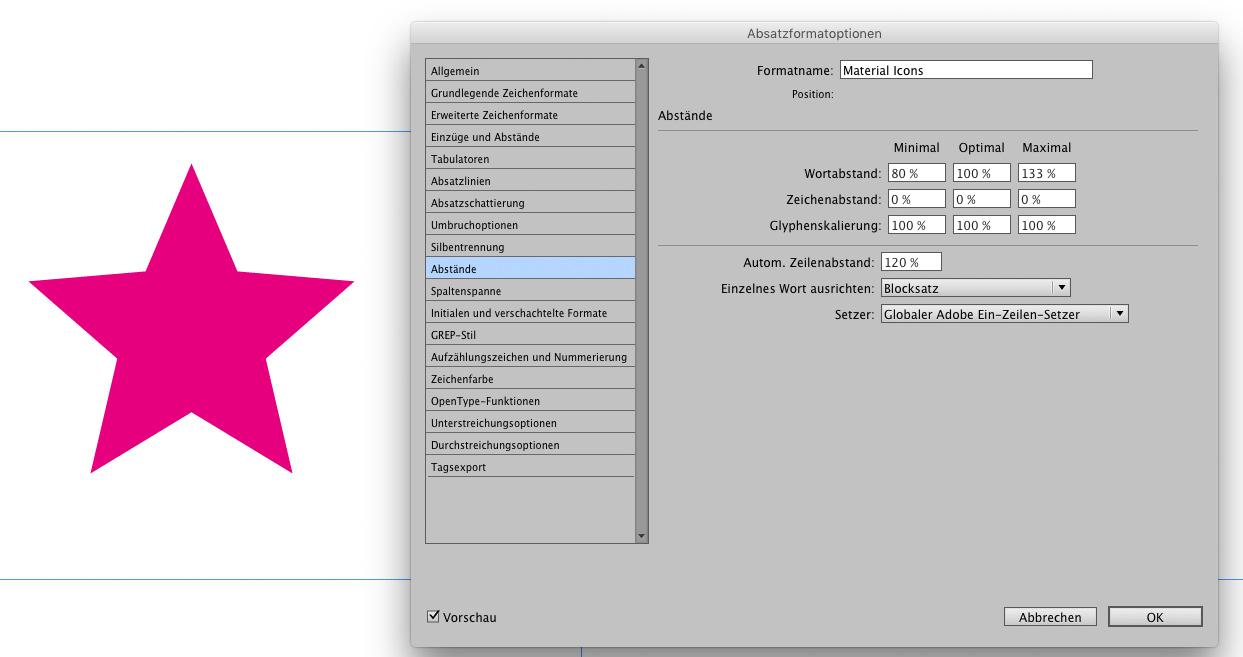
Material Icon Font im InDesign
ich bin ja ein großer Freund des cleveren Iconfonts Ligature Symbols von Kazuyuki Motoyama, weil sich der mit der Ligaturfunktion so wunderbar im InDesign verwenden lässt.
Begriff tippen --> Icon kriegen. Fein.
Deshalb habe ich mich gefreut, als ich gelesen habe, dass der neue Material Icon Font von Google auch so verwendet werden kann. Das funktioniert auch ganz prächtig im Photoshop – leider stellt InDesign* die Zeichen, aus denen die Ligatur zusammengestellt wird, mit kleinen Outline-Rechtecken dar.
Weiß jemand, warum das so ist?
Ich habe die .ttf über die Schriftensammlung aktiviert.
Ich vermute, das liegt daran, daß dem Font das Leerzeichen fehlt. InDesign ersetzt bei einer Ligatur die weggefallenen Glyphen durch Leerzeichen, das in diesem Font, weil es nicht enthalten ist, durch das "notdef"-Kästchen dargestellt wird.
Vermutlich sehr naive Frage an den Profi: Kann man das Leerzeichen denn unproblematisch mit Fontographer oder Glyphs in den Zeichensatz "randengeln"?
Ich vermute, das liegt daran, daß dem Font das Leerzeichen fehlt. InDesign ersetzt bei einer Ligatur die weggefallenen Glyphen durch Leerzeichen, das in diesem Font, weil es nicht enthalten ist, durch das "notdef"-Kästchen dargestellt wird.
Das hatte ich auch erst vermutet, die Vermutung dann aber wieder verworfen, weil .notdef in diesem Font ganz andere Proportionen hat als im Screenshot. Und was das ID-Verhalten angeht, verstehe ich nicht, wie das im Normalfall funktioniert. Entstünden keine Lücken im Text, wenn wegfallende Glyphen durch das normale Leerzeichen (U+0020) ersetzt würden? Oder meinst du etwa das nullbreite »Leerzeichen« (U+2008)? Das bringt aber lange nicht jeder Font mit, sodass dieses Problem wohl öfter auftreten sollte? :-?
Kann man das Leerzeichen denn unproblematisch mit Fontographer oder Glyphs in den Zeichensatz "randengeln"?
Ist zwar etwas spät, aber ich stand gerade vor dem selben Problem und habe einen relativ simplen Workaround gefunden, dass die Icons zumindest korrekt in InDesign verarbeitet werden können – nur leider ohne die praktische Ligaturfunktion, sondern anhand der Glyphen-Palette.
Man kann die Icons in Illustrator "schreiben" und dann per Copy & Paste bei InDesign in den gewünschten Textkasten einfügen. Das Icon wird in InDesign weiterhin als Text behandelt und man kann es in wie gewünscht be- und verarbeiten. Keine Ahnung warum es so funktioniert, aber es funktioniert, wenn auch etwas umständlich!
der Workaround hat beim mir leider nicht funktioniert – ich habe aber gerade durch Zufall die Lösung für das Problem gefunden:
Die rätselhaften Kästchen verschwinden, sobald die Option Globaler Ein-Zeilen-Setzer bzw. Globaler Adobe-Absatzsetzer (über die Absatzformatvorlagen unter "Abstände" oder direkt im Kontextmenü der Absatz-Palette) aktiviert wird.
Die Rechtecke könnten sich überlagende .notdef-Zeichen sein.
Ich vermute, dass das Problem nicht entstünde, wenn die Zeichen a–z und underscore die Breite Null hätten. Sie haben aber eine Breite von 512 Einheiten. Wenn du „lightbulb_underscore“ eingibst, versucht Indesign, das „Wort“ wahrscheinlich zu trennen, bevor das OpenType-Ligatur-Feature greift, denn 20 Zeichen mit einer Breite von 512 Einheiten passen bei einem großen Schriftgrad nicht unbedingt in eine Zeile.
Keine Ahnung, warum die Rechtecke bei dir in Indesign auch unter das Glühbirnen-Icon gezogen werden. Hast du da eventuell am Zeichenabstand (Lauweite/Kerning) rumgespielt und außer dem Code für das Glühbirnen-Icon noch weitere Zeichen eingegeben? Wie auch immer. Das Problem müsste sich leicht beheben lassen:
Du könntest den Font mit TTX dekompilieren und die Breite der Zeichen a–z und Underscore auf den Wert 0 setzen. Ebenso den Wert für lsb (left side bearing). TTX ist kostenlos und im AFDKO (Adobe Font Development Kit for OpenType) enthalten.
Mal abgesehen davon würde es Sinn machen, die Zeichen, die das Ligatur-Feature ersetzen soll, mit einer Outline zu versehen. Sonst weiß man ja gar nicht, welche und wie viele Zeichen man eingetippt hat. Wenigstens ein Bullet als Dummy, damit man weiß, wie viele Zeichen man eingegeben hat, bevor das Ligatur-Feature greift. Oder z. B. mittig platzierte Buchstaben mit geringer Breite (150 bis 200 Einheiten).
Fuß feet        Ei egg        China china
Ähre ear        Schere scissors    Pferd horse
Ölsardine can     Sparschwein piggybank    Augen eyes
Auto Trabant car    Buch book    Stern star
Eule owl        Faß barrel    Schaf sheep
Ziege oat    Eber boar    Sau sow
Ferkel piglet    Kuh cow cattle    Hengst stallion
Hahn rooster    Huhn chicken    Küken chicklet
Hase rabbit    Möwe seagull
Zusätzlich gibt der Font bei Zahleneingabe jeweuils für 2 Ziffern einen Dominostein aus.